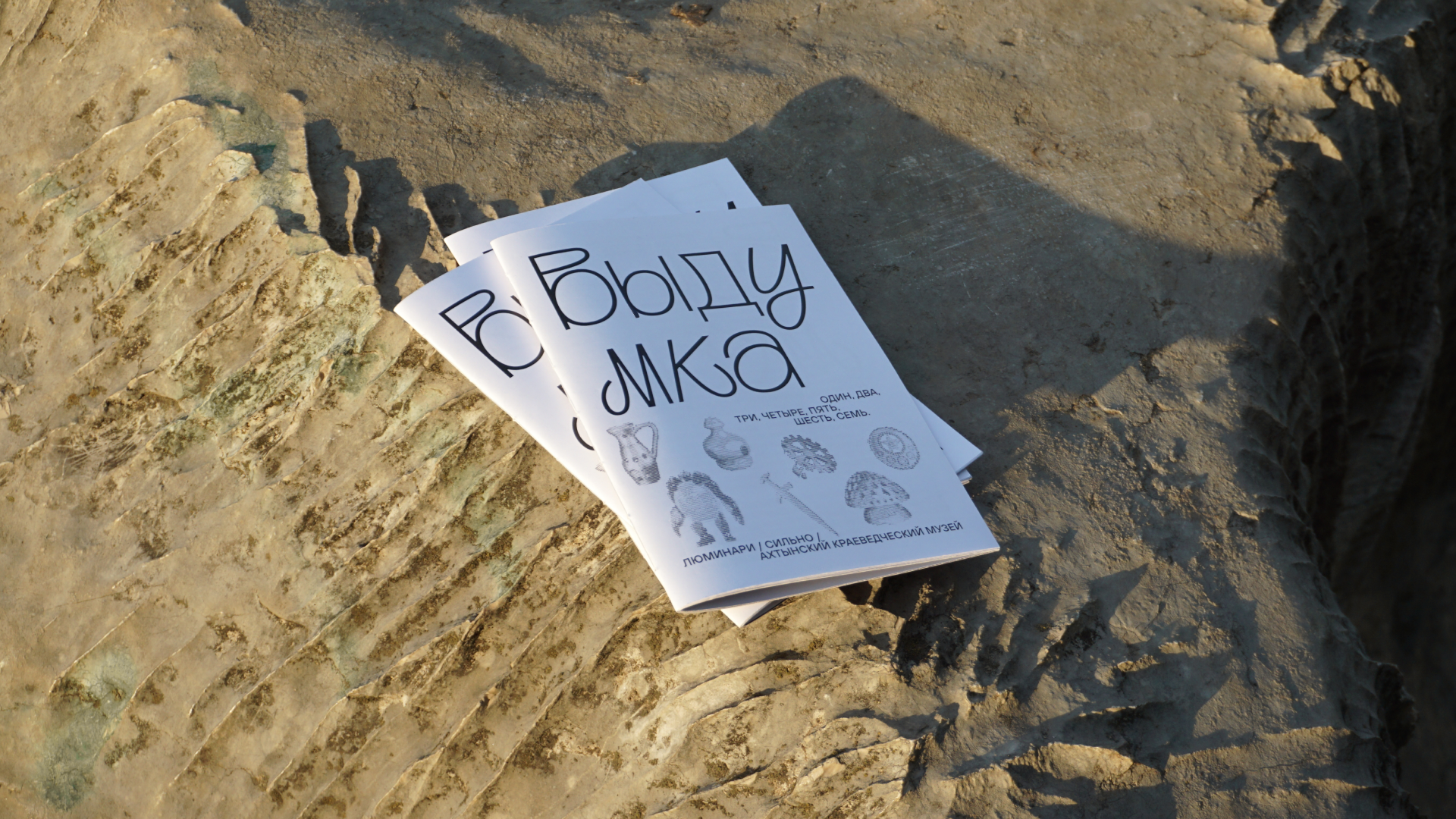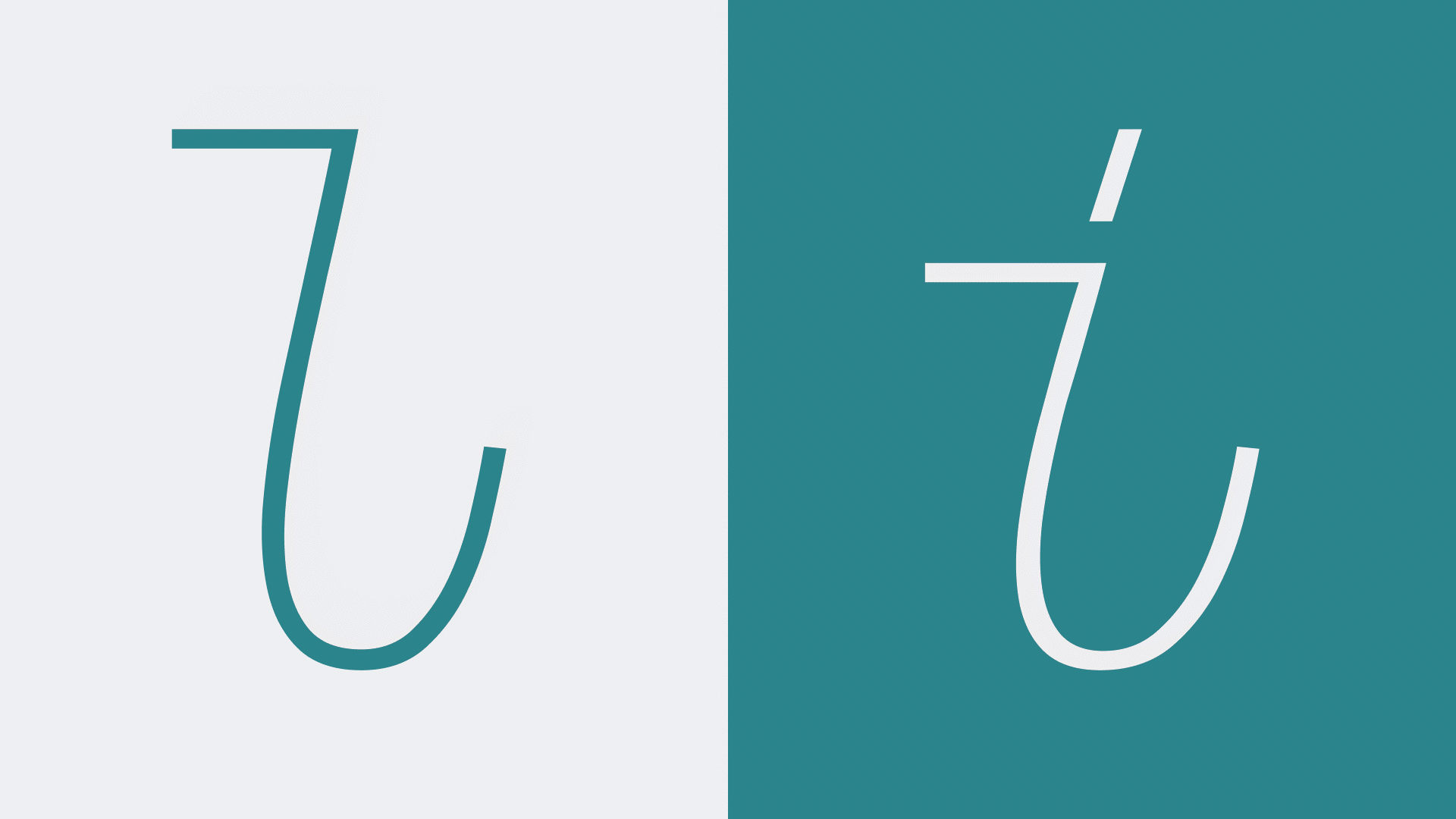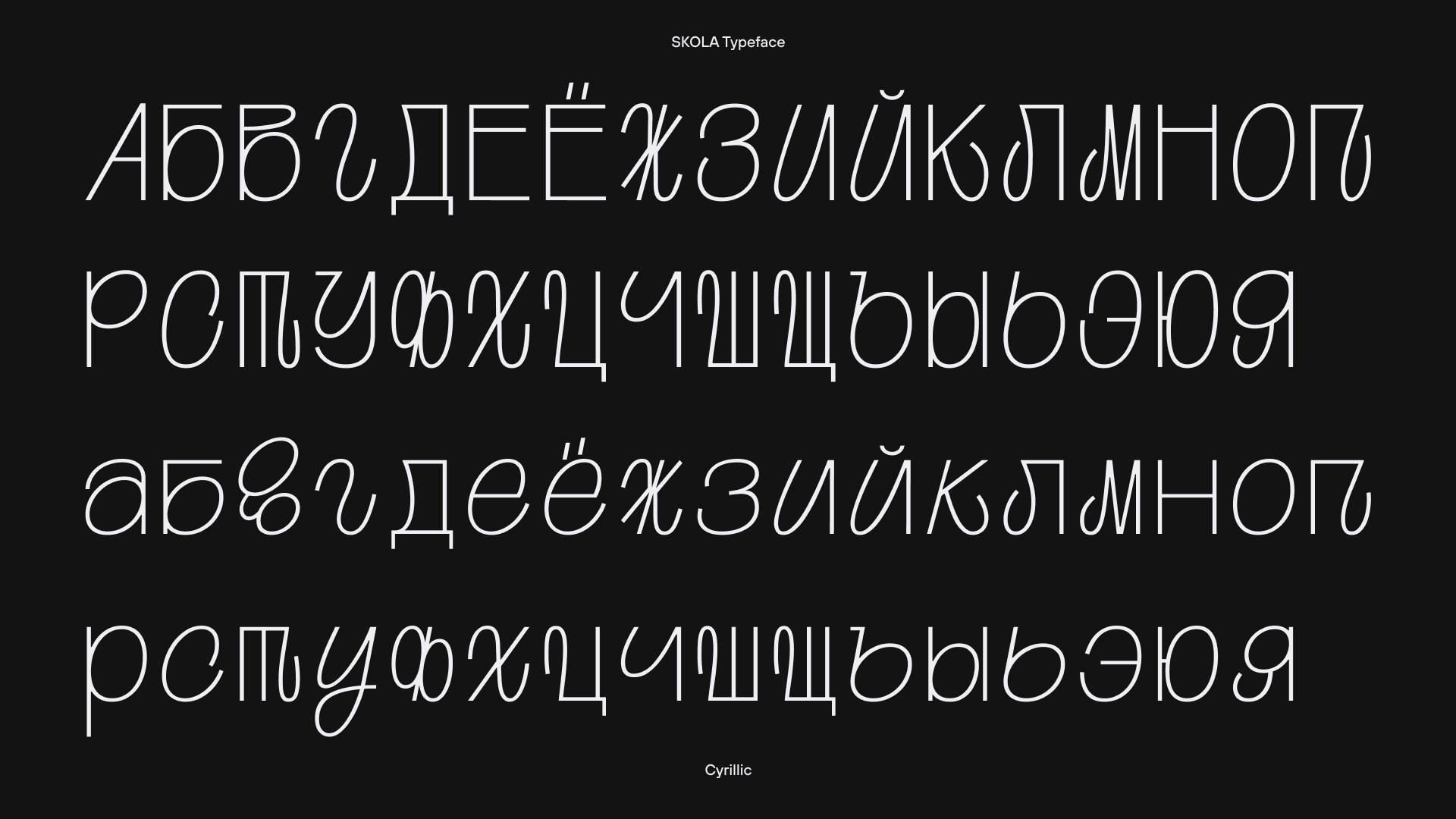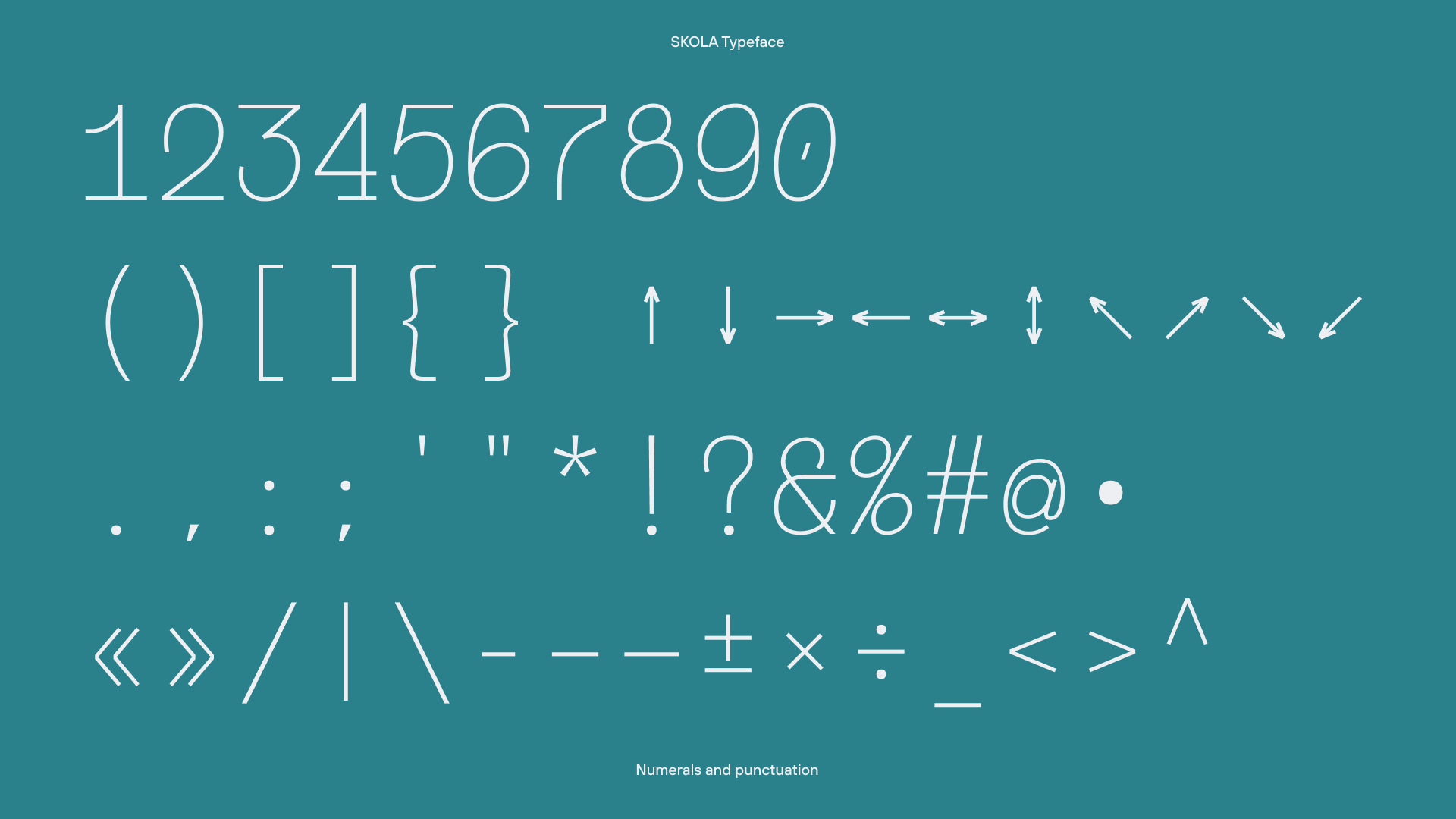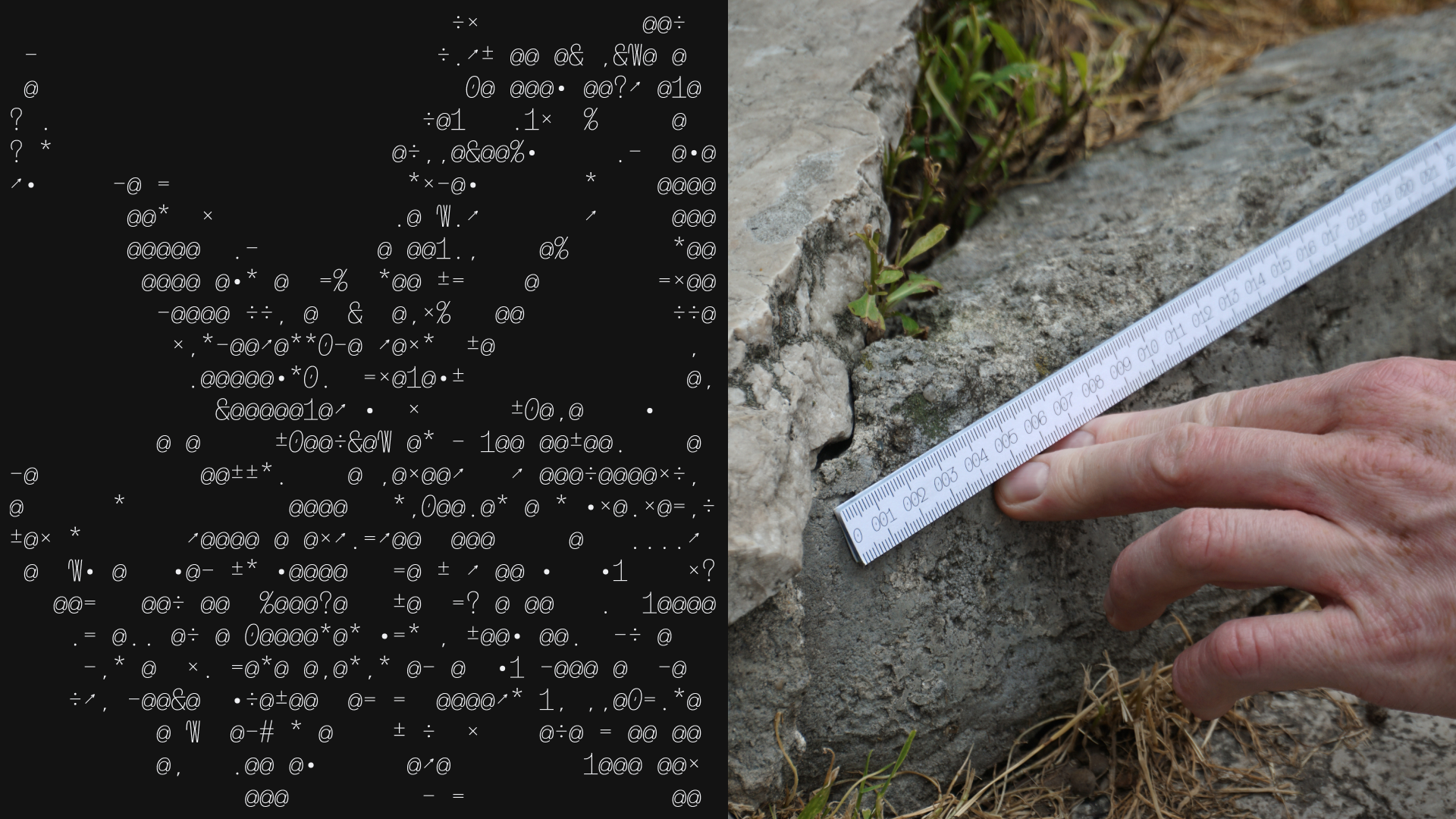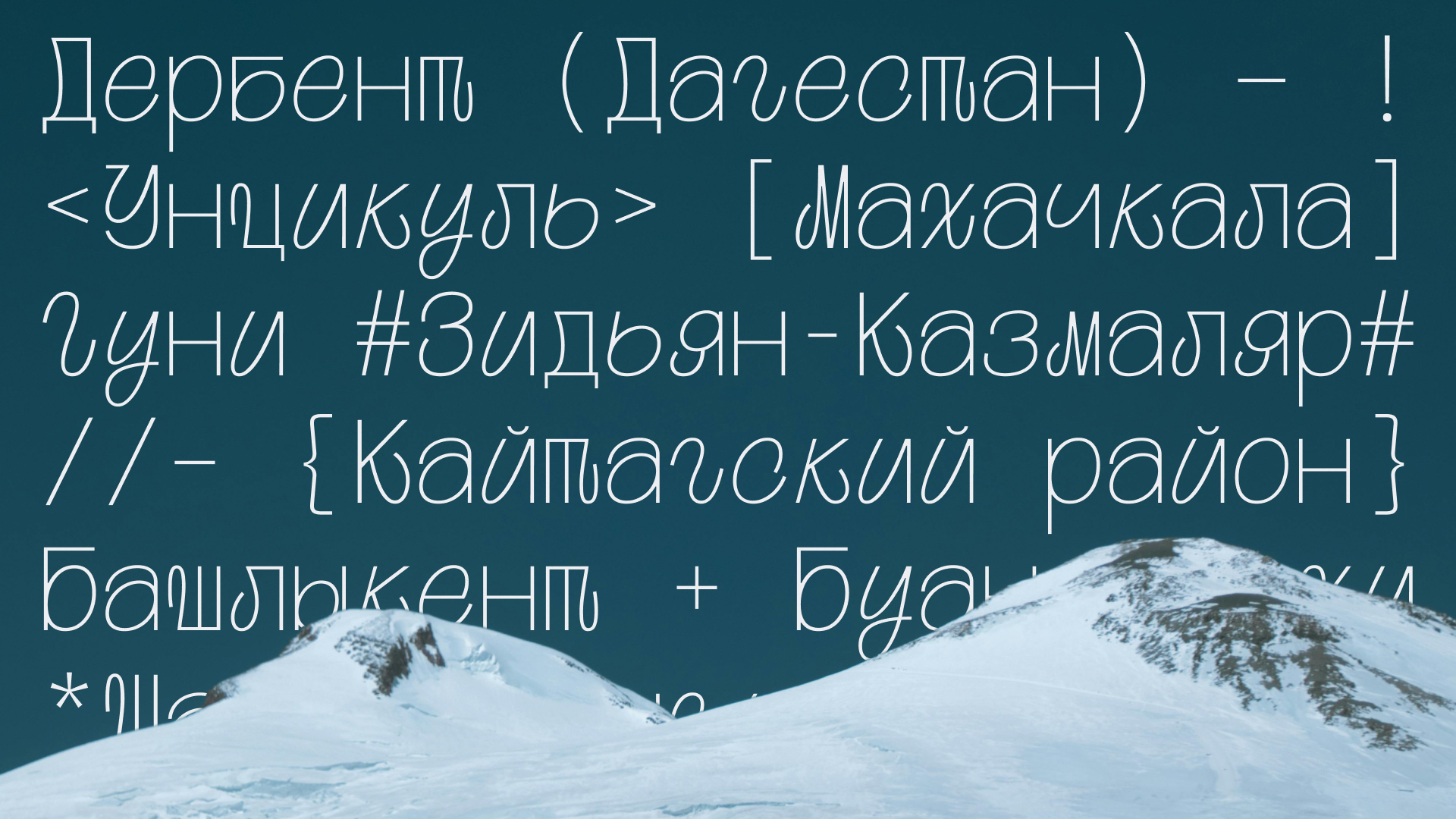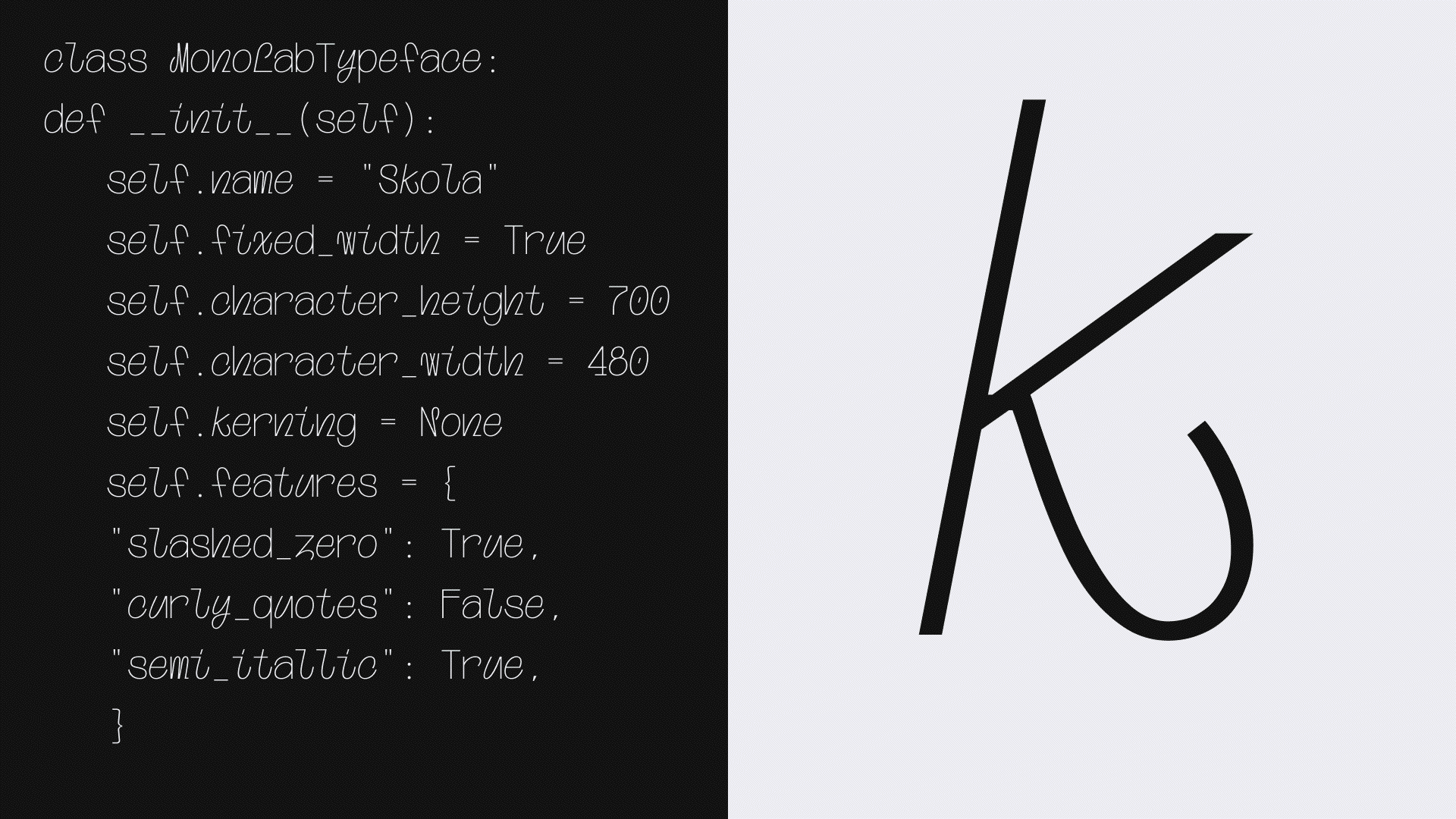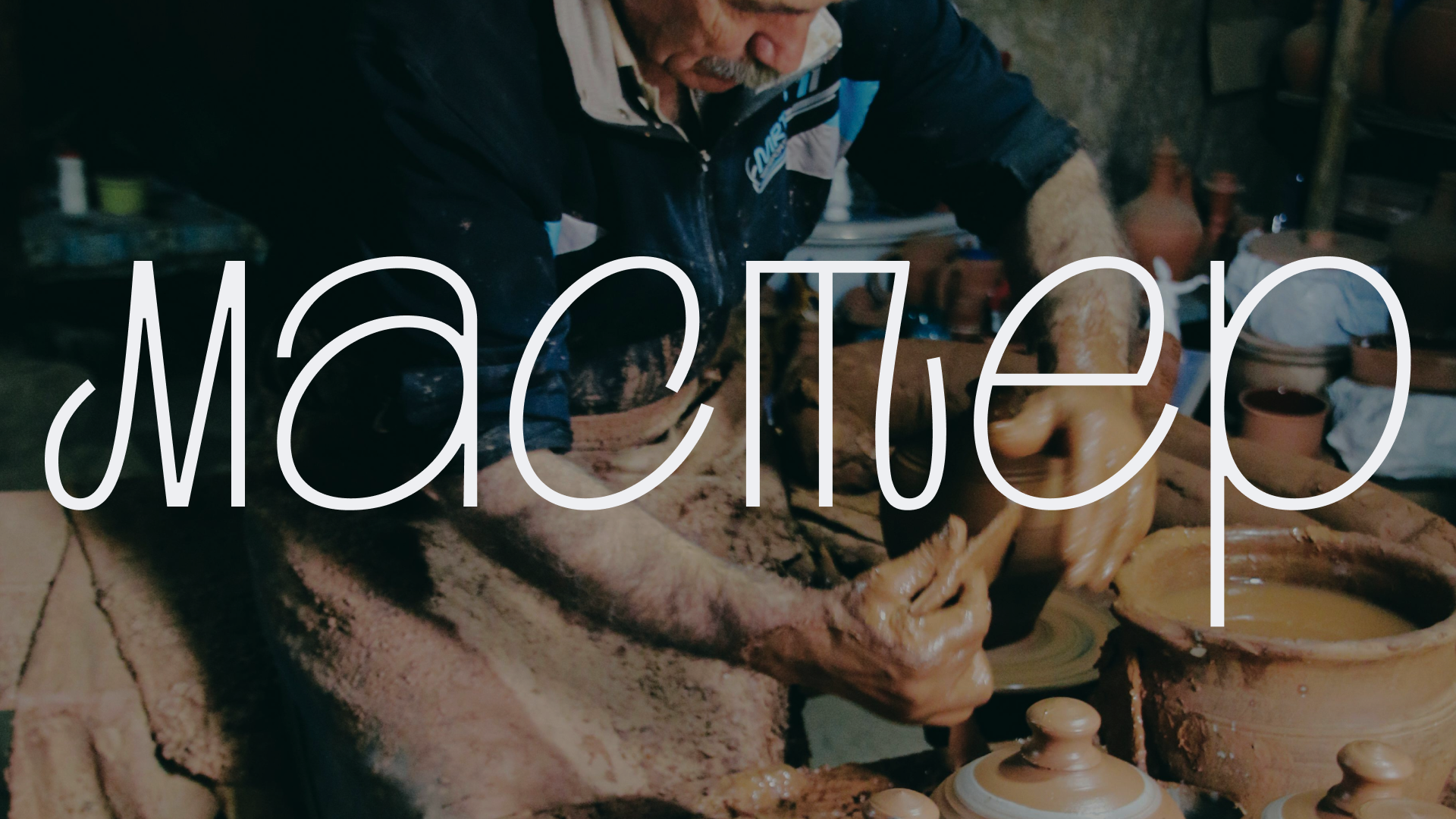
Экспериментальный шрифт
Škola
Кастомный шрифт для айдентики образовательных спецпроектов арт-резиденции в Дагестане. Шрифт вдохновлён школьными прописями и повторяет естественные мягкие формы природы региона.
Резиденция «Сильно»